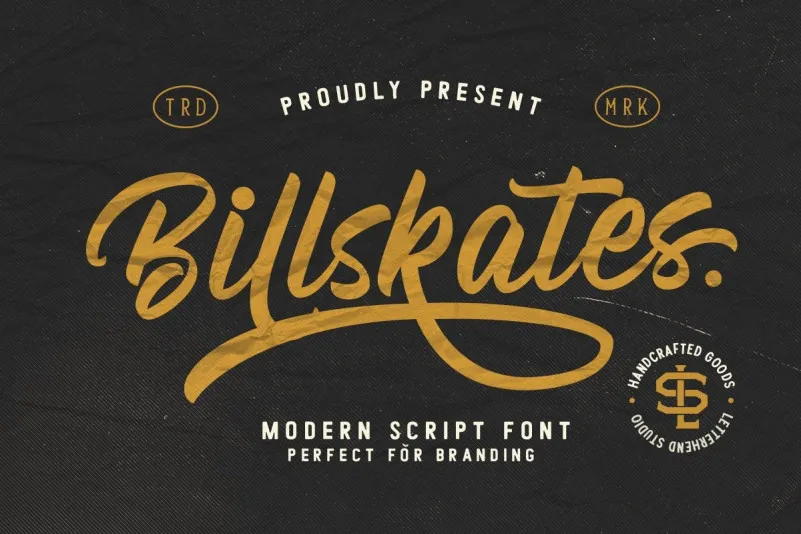
Billskates Script Font – Download Grátis
Billskates Script Font é uma elegante nova tipografia moderna que une elementos atraentes de escrita original com formas modernas frescas. Desenvolvida pela Letterhend Studio, essa fonte combina traços bold e estilos de letras manuscritas inspirados em arte gráfica manual, criando um resultado único e profissional. Com sua versatilidade incrível para logos, cartões de visita, embalagens, livros e mais, a Billskates Script Font é perfeita para qualquer projeto que precise de uma pitada de sofisticação e originalidade. Ela será o complemento ideal para tornar seus trabalhos gráficos mais profissionais e atraentes. Seja você designer, publicitário ou criativo, não há dúvida de que essa fonte trará um novo nível ao seu trabalho, com sua rica herança de estilo moderno em uma linguagem única e inspiradora.